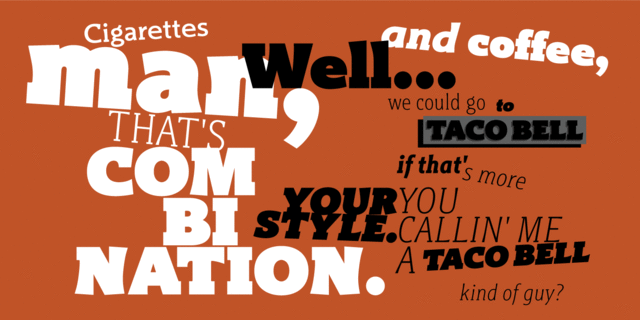
Гарнитура шрифтов Titla Brus (Титла Брусковая) разработана в развитие гарнитуры Titla, выпущенной в 2009 году. Брусковая гарнитура состоит из двадцати начертаний нормальных и узких пропорций шести насыщенностей и рассчитана как на совместное использование со шрифтом Titla, так и в качестве самостоятельной акцидентной гарнитуры. Рисунок шрифта имеет довольно оригинальный характер, выражающийся в использовании брусковых засечек. Они могут быть двусторонними, односторонними и их может вообще не быть там, где они обычно бывают. Это придает шрифту немножко необычный характер и своеобразие. Шрифт разработан Олегом Карпинским. Выпущен компанией ПараТайп в 2011—2013 годах сначала в комплекте десяти узких начертаний, а позже в расширенном виде с дополнением десяти нормальных начертаний.